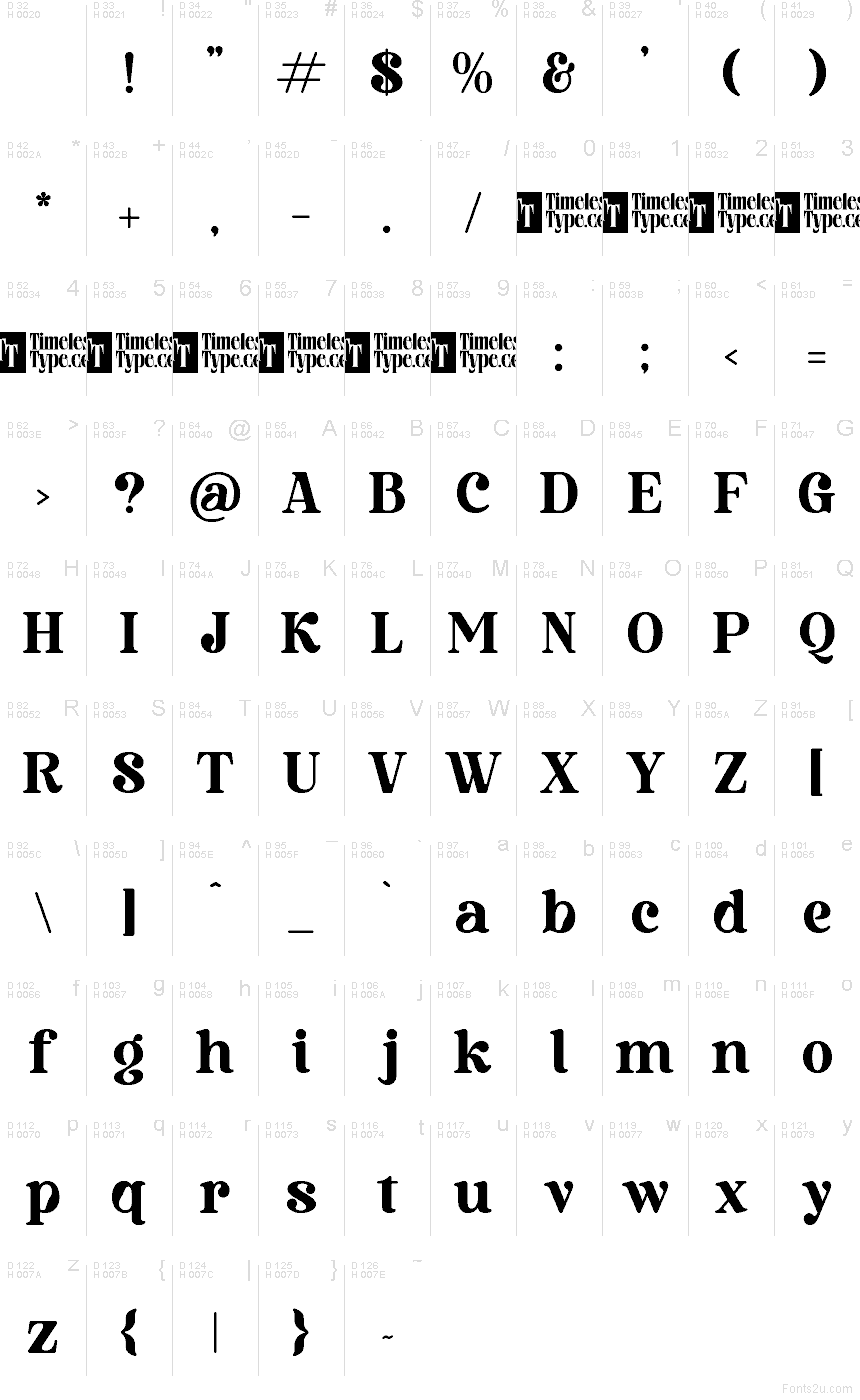
Eleve os seus projetos de design com Font Bruge Vibes - Bold Alternate Serif Font Serif Display, uma fonte tipográfica criada para atrair todos os olhares e transmitir um charme sofisticado. Esta envolvente fonte display reúne uma presença marcante, serifas elegantes e exclusivas e curvas refinadas, resultando num estilo tipográfico verdadeiramente singular. Os seus traços de elevado contraste garantem o máximo impacto visual, tornando-a a opção ideal para projetos que exigem uma estética imediata e inesquecível.
Desfrute de uma liberdade criativa sem precedentes graças aos inúmeros recursos de Font Bruge Vibes - Bold Alternate Serif Font Serif Display. Com uma impressionante seleção de 16 ligaduras expressivas e 69 glifos alternativos exclusivos, esta fonte abre portas a infindáveis possibilidades na criação de títulos sob medida, logótipos e peças de identidade visual. Estes complementos cuidadosamente concebidos permitem que designers personalizem cada caractere, criando composições dinâmicas e originais que se destacam naturalmente.
Amplie o alcance e o prestígio global da sua marca através da notável versatilidade de Font Bruge Vibes - Bold Alternate Serif Font Serif Display. Graças ao seu suporte alargado a múltiplos idiomas, Font Bruge Vibes - Bold Alternate Serif Font Serif Display adapta-se com naturalidade a diferentes mercados, revelando-se uma ferramenta indispensável para projetos internacionais. Esta funcionalidade essencial permite que a sua mensagem seja comunicada com clareza e elegância, superando barreiras linguísticas com facilidade.
Encontre em Font Bruge Vibes - Bold Alternate Serif Font Serif Display a solução tipográfica ideal para marcas premium e mensagens marcantes. É perfeita para marcas de luxo, embalagens requintadas, design editorial, moda e qualquer aplicação que exija títulos distintos ou uma identidade com personalidade. Escolha esta fonte para conferir aos seus trabalhos um toque inequívoco de prestígio, assegurando destaque à sua marca com histórias visuais inesquecíveis.